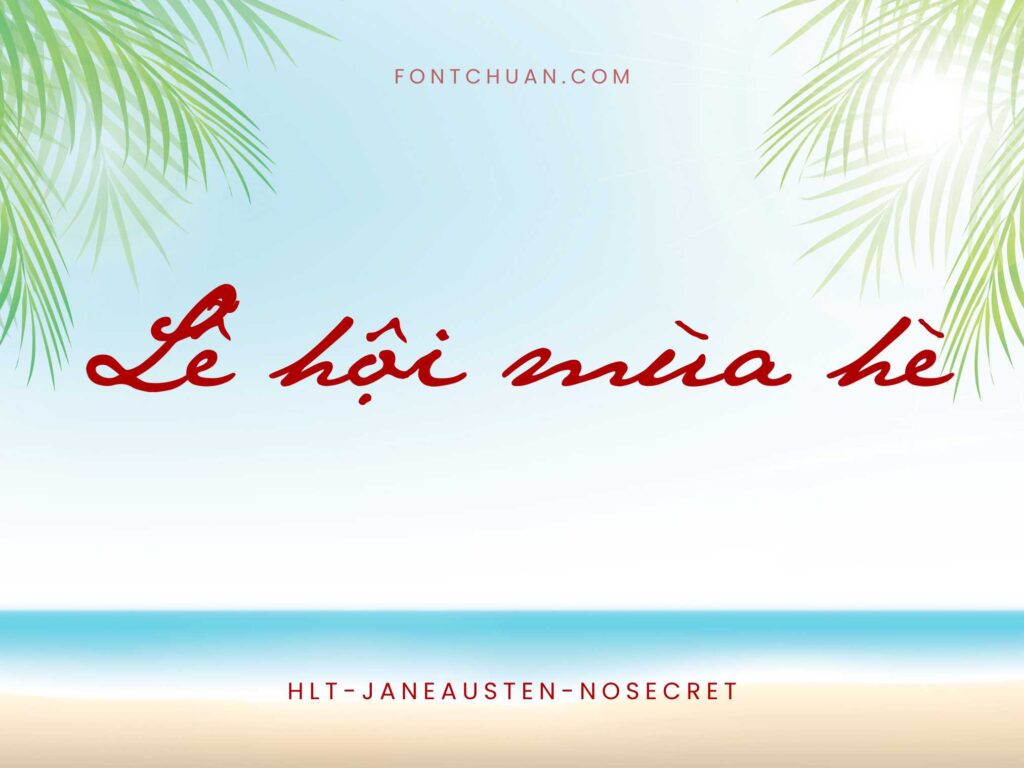
Font HLT Janeausten Nosecret Việt Hóa
Jane Austen là một phông chữ thư pháp được thiết kế bởi Pia Frauss, lấy cảm hứng từ chữ viết tay của nữ văn sĩ nổi tiếng người Anh, Jane Austen. Phông chữ này mang phong cách cổ điển và thanh lịch, với các đường nét mềm mại và uyển chuyển, tạo nên sự tinh tế và trang nhã cho các thiết kế. Với sự Việt hóa của HLT, Jane Austen hỗ trợ đầy đủ các ký tự tiếng Việt, giúp người dùng dễ dàng áp dụng trong các dự án đa ngôn ngữ. Thành viên của Font Chuẩn đã sưu tầm và chia sẻ phông chữ này nhằm đáp ứng nhu cầu đa dạng của cộng đồng thiết kế.
Về đặc điểm thiết kế, Jane Austen sở hữu các ký tự được thiết kế tỉ mỉ, mang lại cảm giác nhẹ nhàng và cổ điển. Phông chữ này đặc biệt phù hợp cho các dự án như thiệp mời, bìa sách, poster, logo và các ấn phẩm quảng cáo, nơi cần sự tinh tế và ấn tượng mạnh mẽ. Ngoài ra, Jane Austen cũng thích hợp cho các sự kiện như lễ hội, sinh nhật, Valentine và Trung thu, mang lại không khí lãng mạn và nghệ thuật. Trong lĩnh vực ngành nghề, phông chữ này được ứng dụng rộng rãi trong quảng cáo, thiết kế thiệp cưới, giáo dục và công nghệ, góp phần tạo nên sự độc đáo và thu hút cho các sản phẩm và thương hiệu.